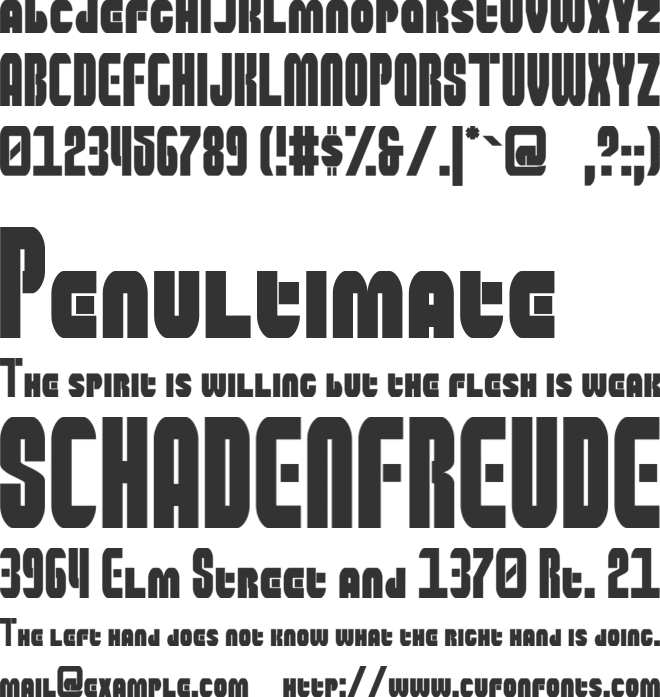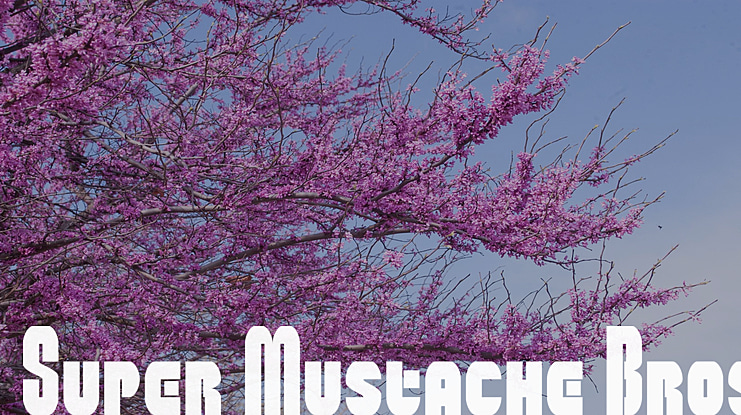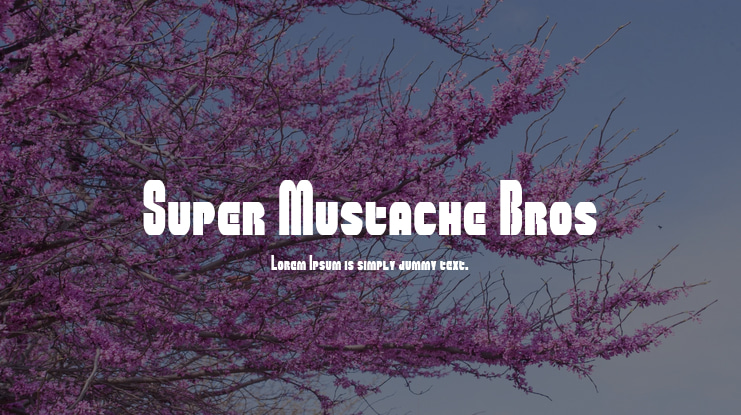
Super Mustache Bros Font
Wagner Salt
Fonte criada com base na logo do Super Mario Bros do Famicom
Esta fonte foi criada baseada no modelo usado pela Nintendo (R) para o jogo Super Mario Bros